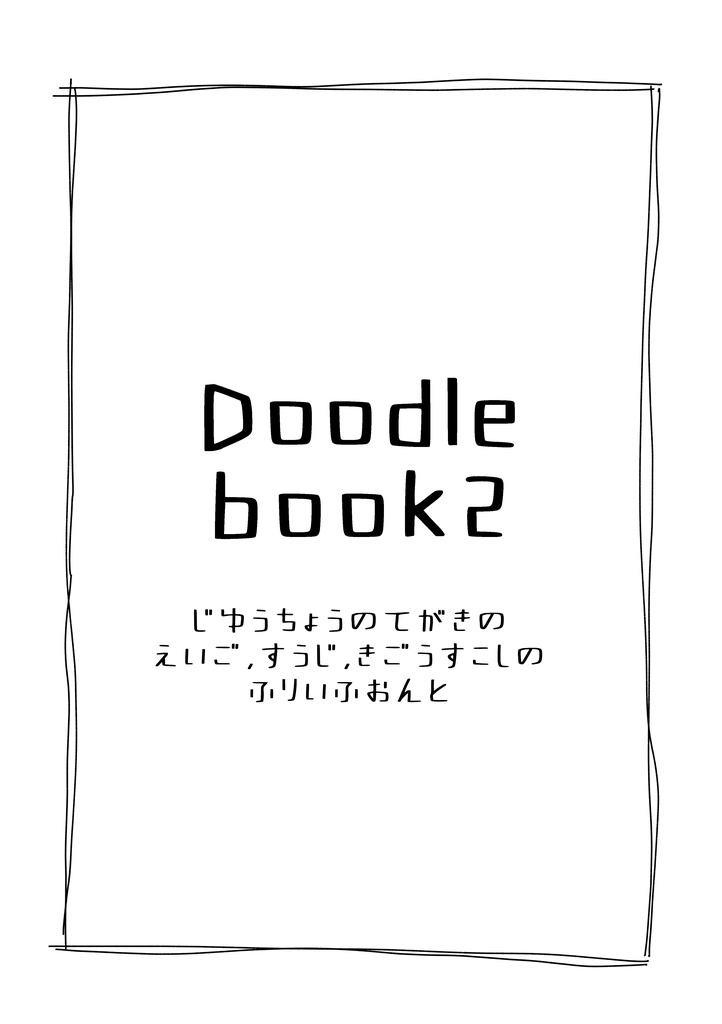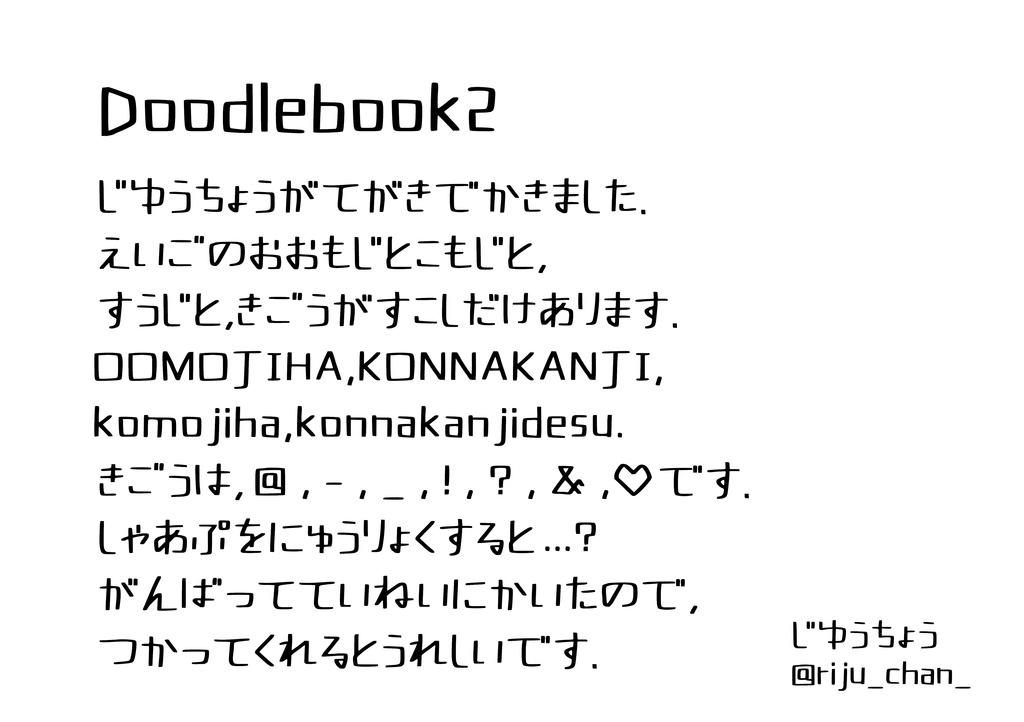
【フリーフォント】Doodlebook2
利き手が腱鞘炎になって絵が描けなくなったので、暇つぶしに手書き文字をフォントにしました。 フリーフォントです。 自分用に作ったので、クオリティは高くないです。 頑張って丁寧に書いたので、使ってくれると嬉しいです。 ☆ひらがなもあるよ!( https://pluie173.booth.pm/items/5053153 ) 〇対応文字 アルファベット大文字小文字、数字、記号少し ・半角で#を入力すると…?何が出るかはお楽しみです。 〇使用可能 ・個人、商用問わず使用可能です。 ・使用報告、クレジット等は不要ですが、していただけるととても嬉しい気持ちです。 〇禁止用途 ・データそのものの二次販売/二次配布 ・変形/加工等をしての二次販売/二次配布 ・自作発言はご遠慮ください。 ・著作権の放棄はしておりません。 使用報告や不備などはX(旧Twitter)(@riju_chan_)、もしくはマシュマロ( https://marshmallow-qa.com/riju_chan_ )へお願いします。